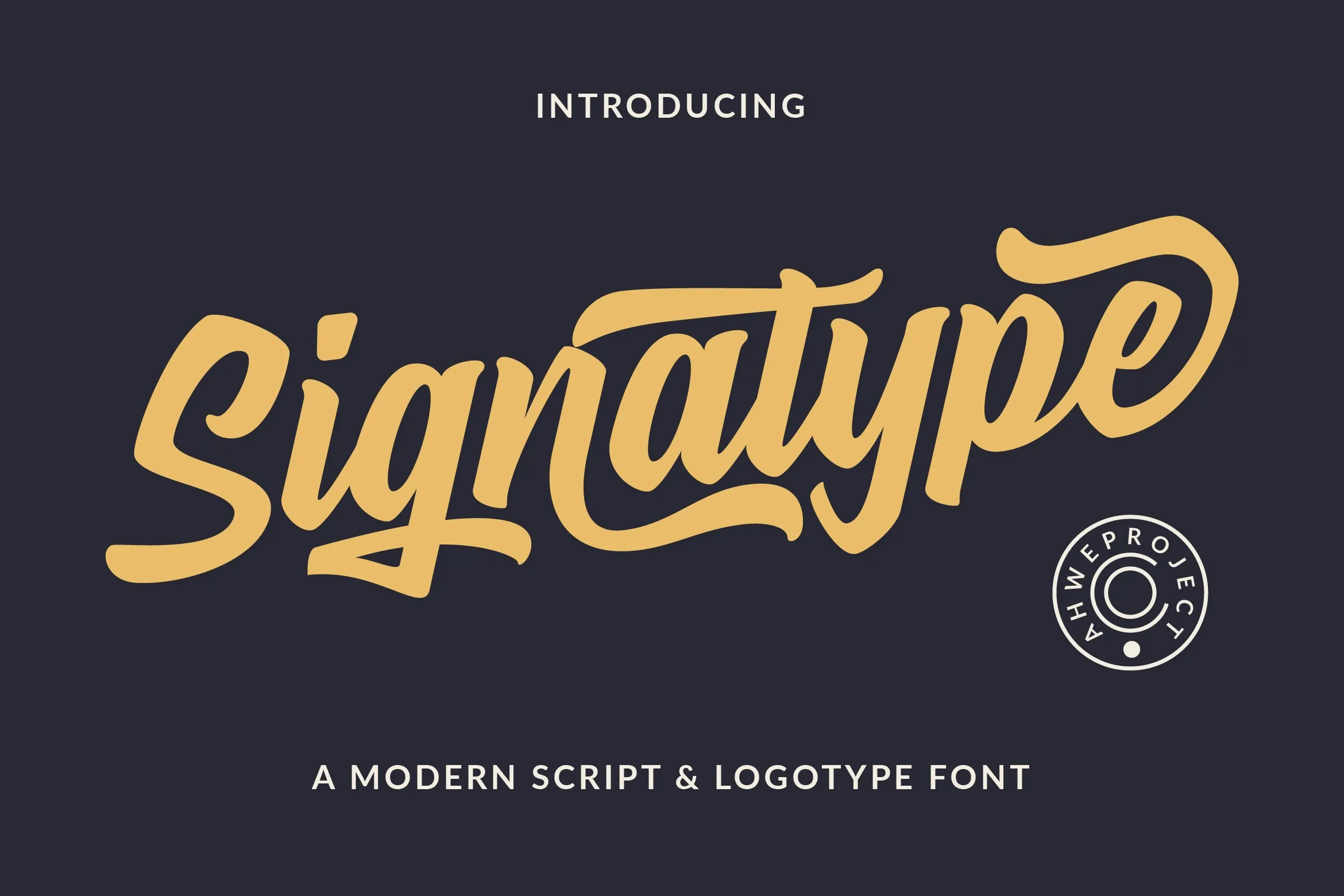
A fonte Signatype Font é uma coleção elegante e versátil para designers que procuram um estilo script sofisticado. Este conjunto de fontes foi projetado para fornecer uma perfeita harmonia entre si, permitindo sua utilização conjunta em qualquer projeto visual. Com suporte a ligaturas e alternativas de caracteres, Signatype Font torna cada design irresistivelmente atraente. Suas letras são belas e bem equilibradas, garantindo que ela se adapte perfeitamente a uma ampla variedade de projetos. Seja para criar um layout minimalista ou artístico extremo, Signatype Font tem o poder de transformar suas ideias mais criativas em algo real e vivido. Adicione essa fonte aos seus desafios design, e você verá como ela os enriquece com sua elegância natural e sofisticação refinada.